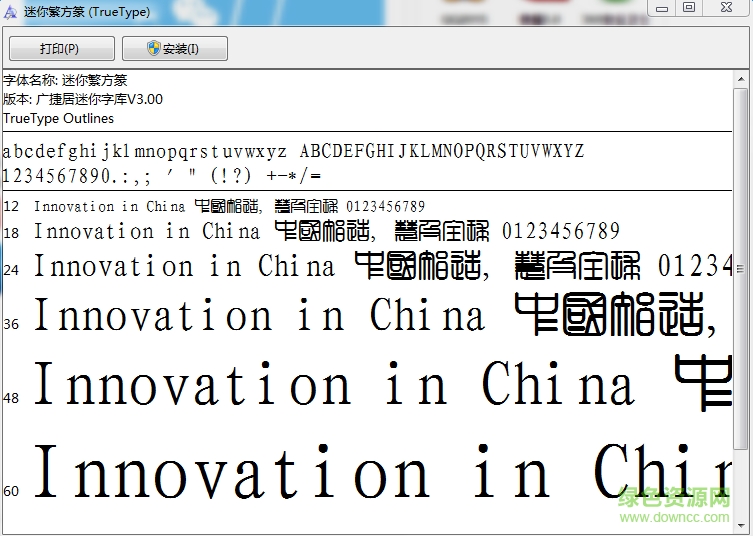
迷你繁方篆字體是一款非常具有藝術(shù)特色的字體,寫(xiě)出來(lái)的字不僅美觀、大方,而且字寫(xiě)出來(lái)的整體效果非常好,用于國(guó)畫(huà)題字方面還是很不錯(cuò)的,小編為大家準(zhǔn)備了下載地址,歡迎有興趣的朋友來(lái)綠色資源網(wǎng)下載。